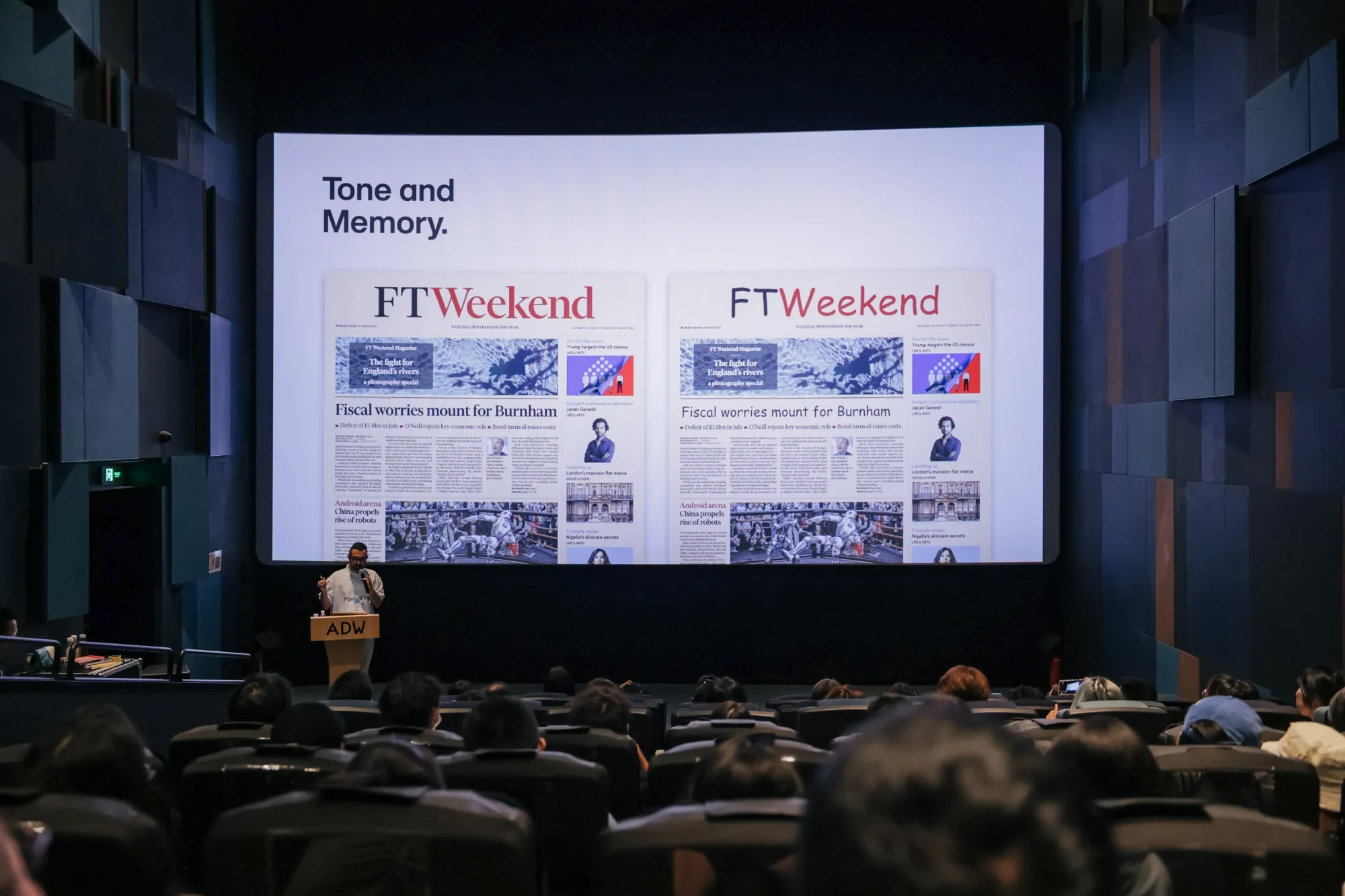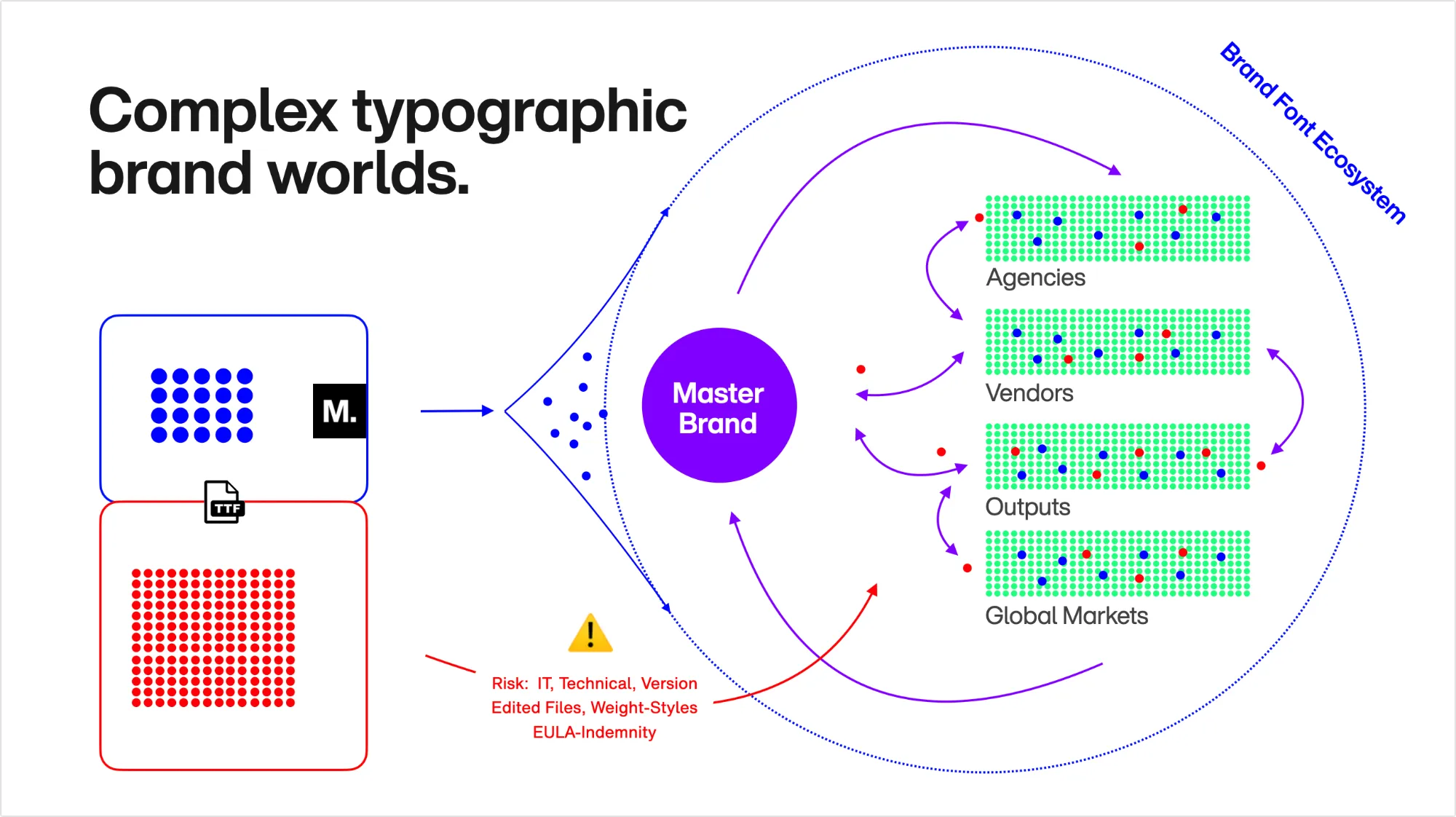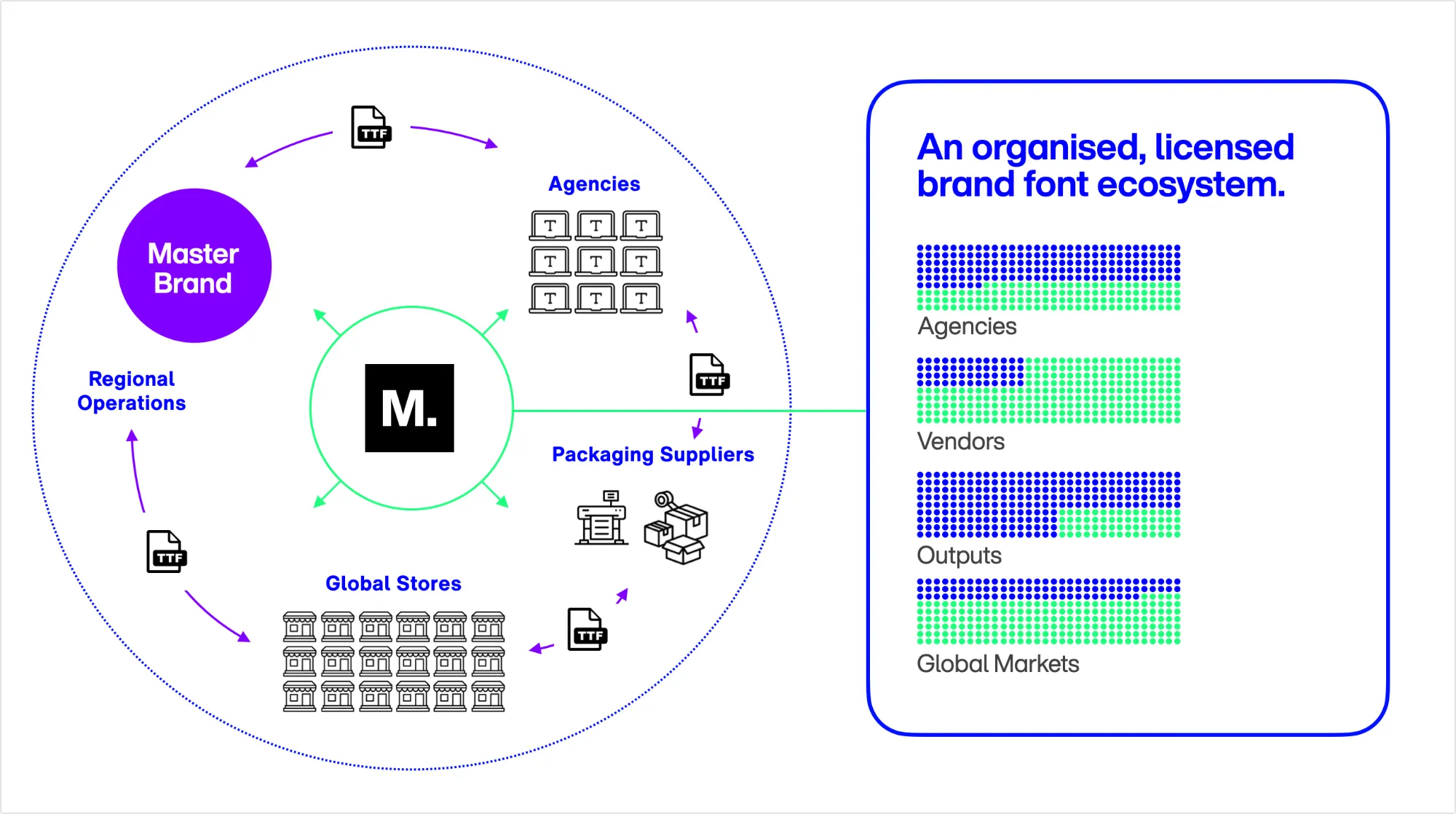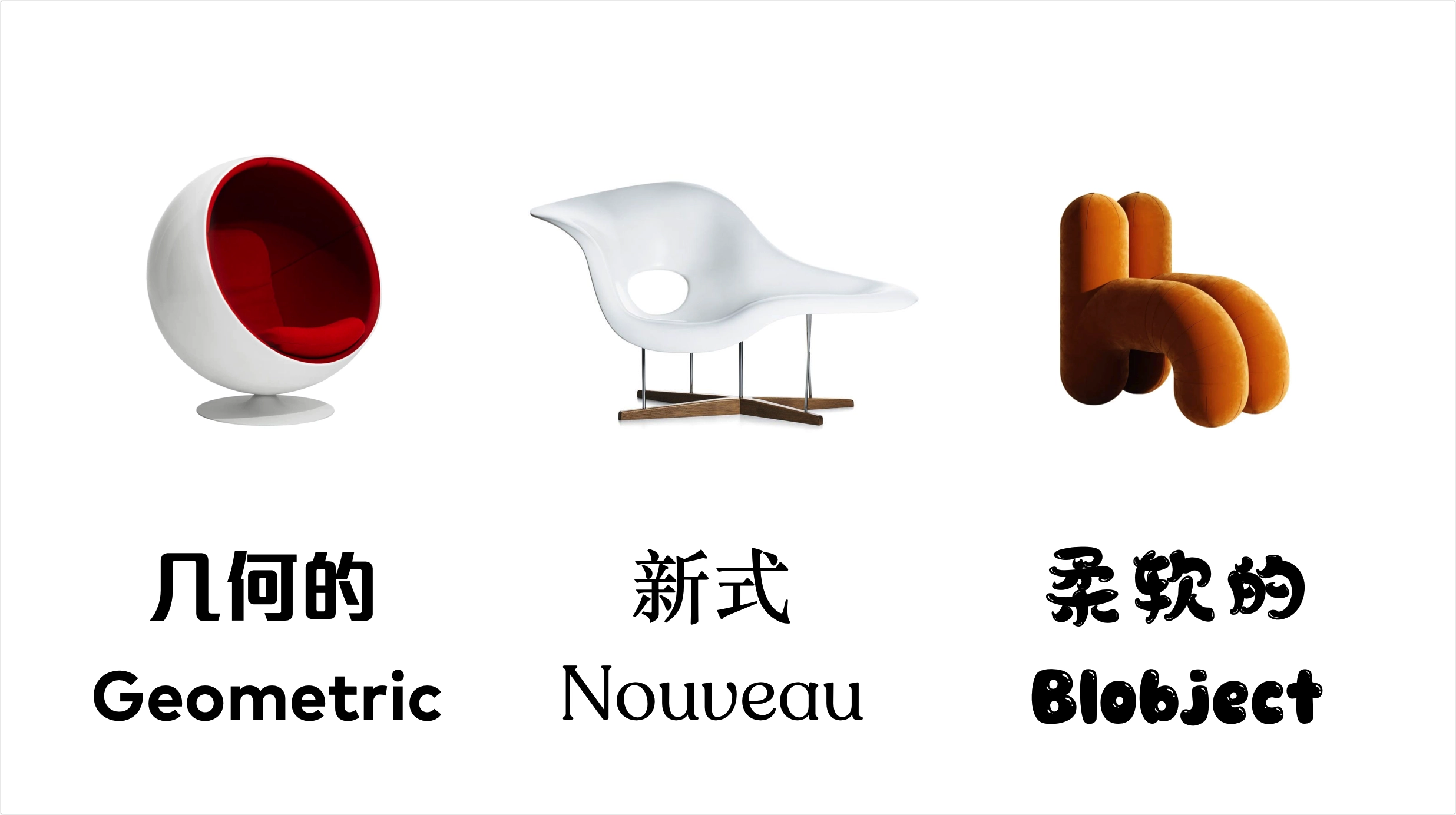
演讲回顾
字体排印
作为文化表达和品牌表现形式
Typography as cultural expression and brand behaviour.
演讲人:Emilios Theofanous,Monotype 执行创意总监 会议:ADW 亚太设计周 2026 时间地点:2026年9月6日,上海复星艺术中心
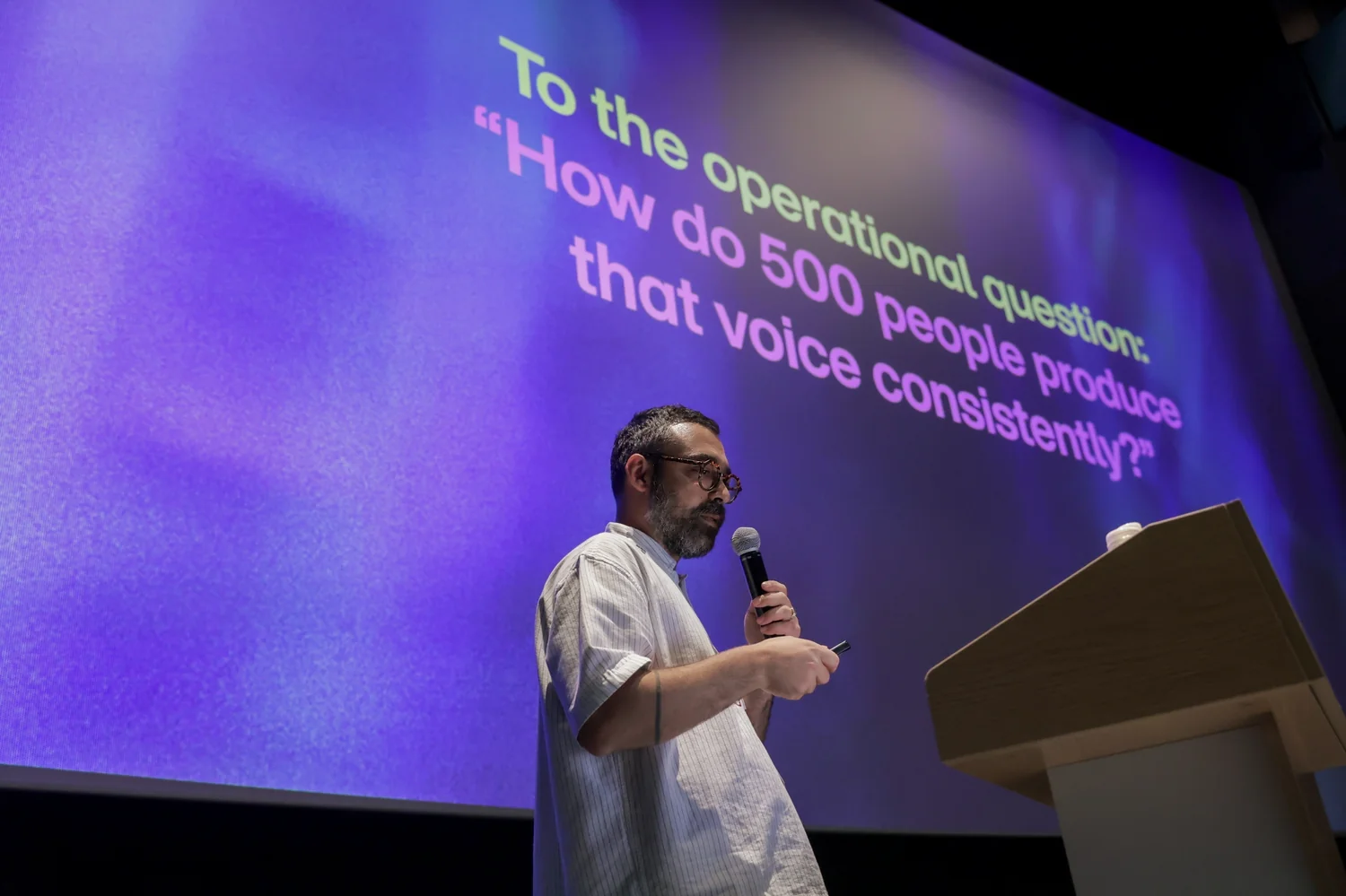
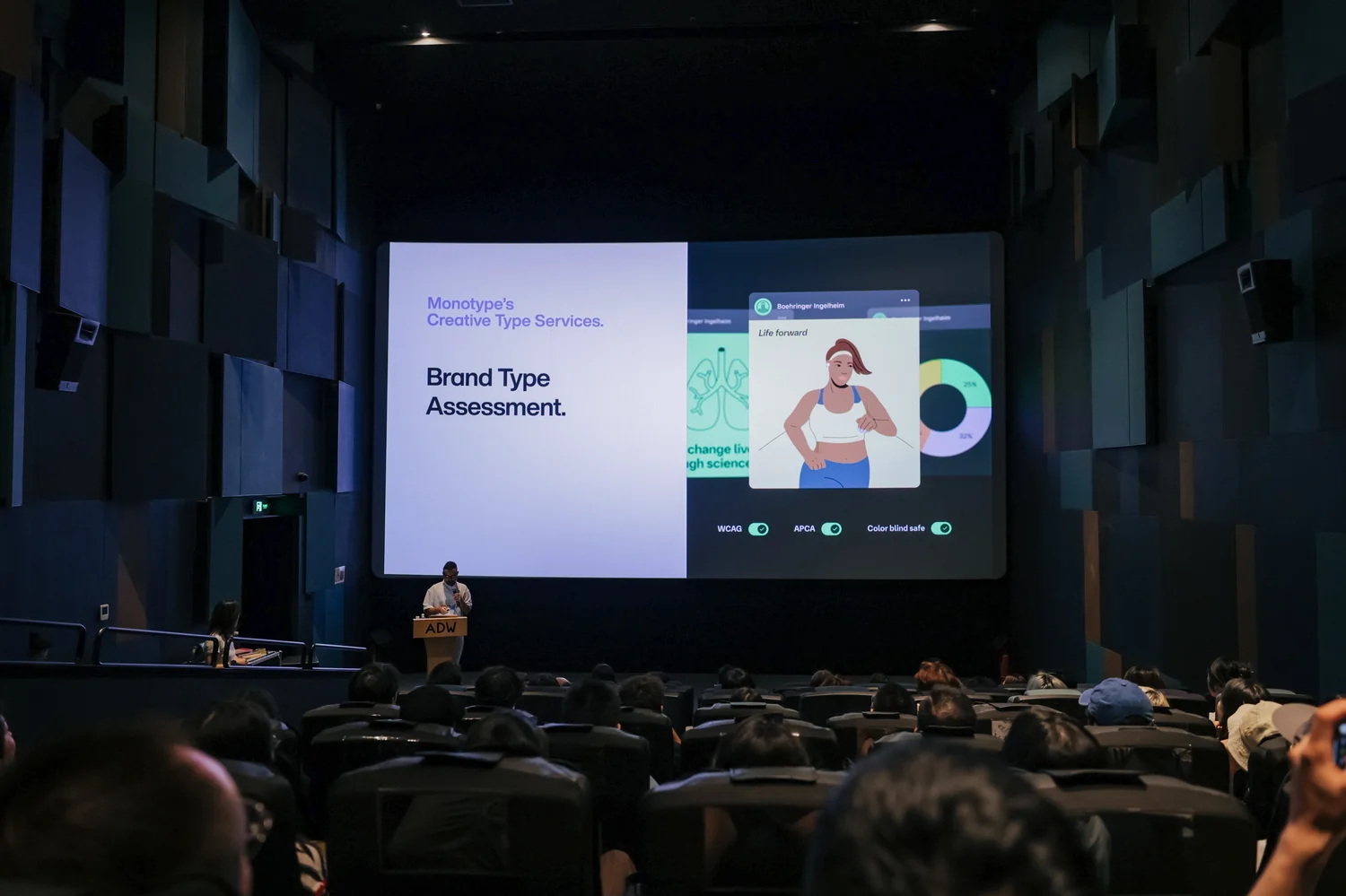
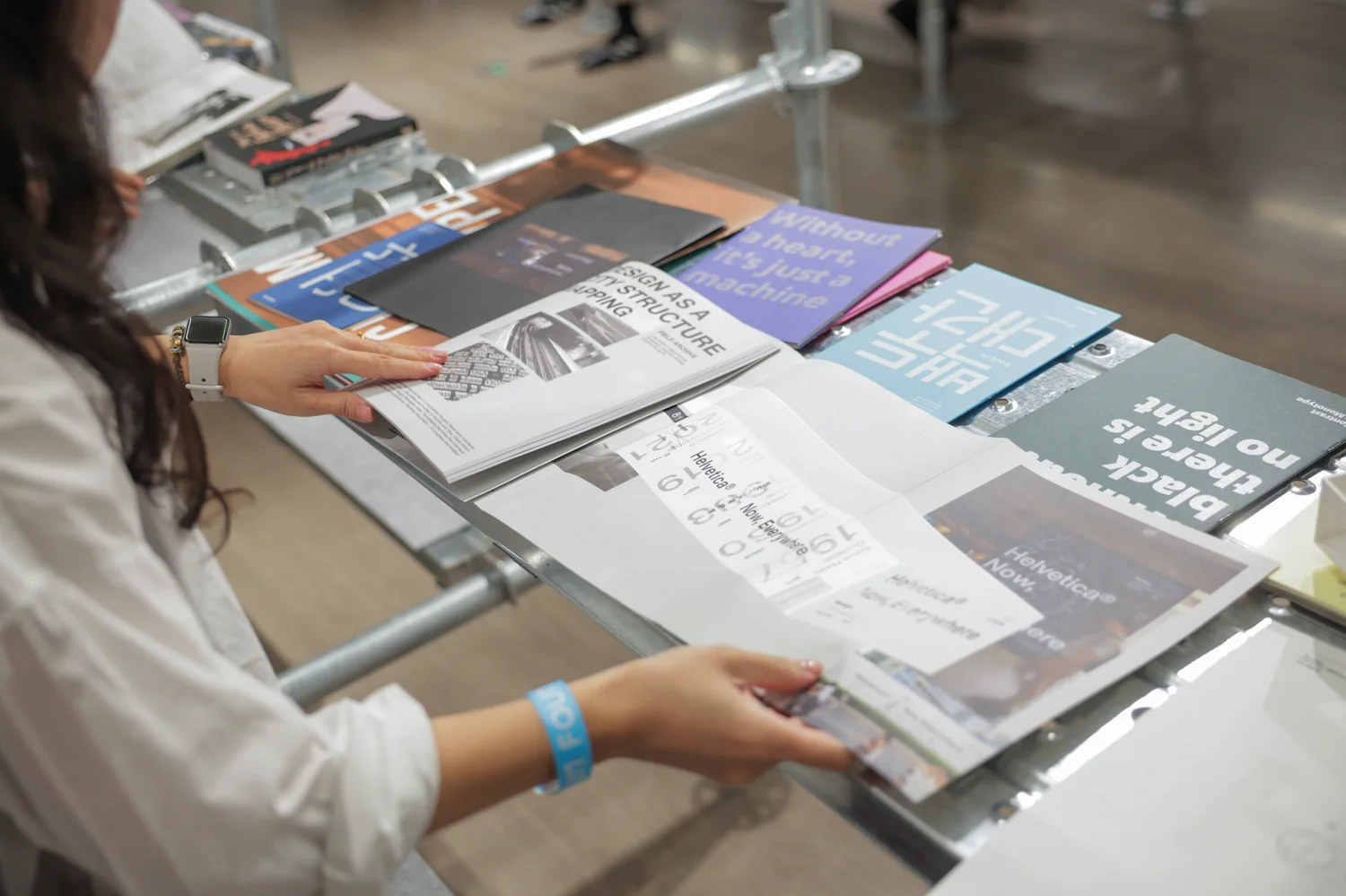
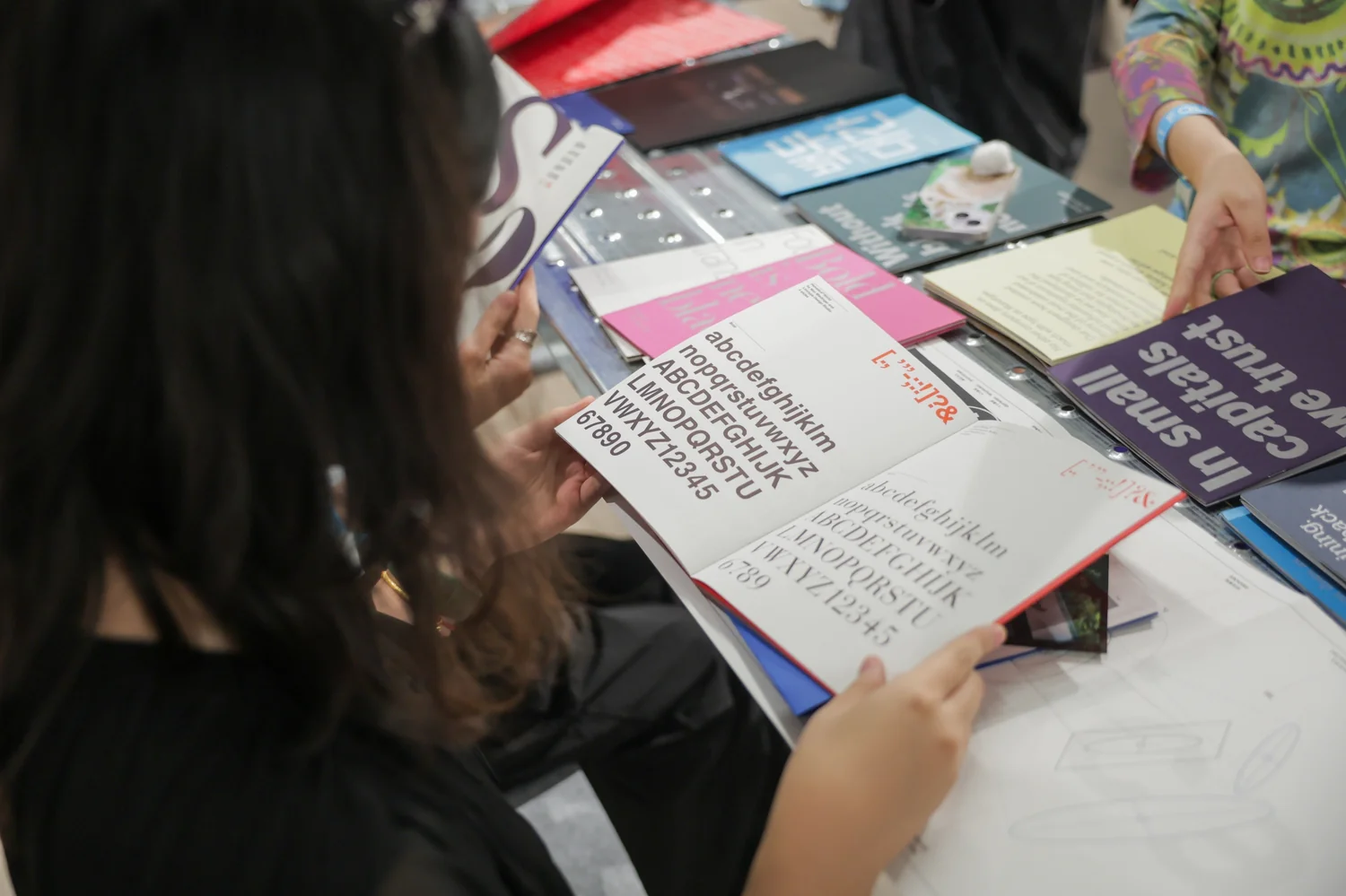
"title": "从 Instagram 改 LOGO 字体到全球字体治理:Emilios 在 ADW 的演讲还聊了什么?"